解构主义是解构主义者德里达的一个术语,是后解构主义提出的一种批判方法,即“结构分解”。人物解构是通过解构对人物本身进行分解、溶解,或者用人物、形象等视觉元素有意识地进行重组、拼贴,以达到特殊的视觉效果。
解构主义崇尚高度的模糊性和无序性,反对现代主义的托辞和二元对立,所以解构的核心是破坏和分解。首先,我们需要忽略后果。抛弃传统审美规律所要求的整体性和统一性,打破整体性,破坏常规规律,形成破碎的空间。打破整体形象和意义,为重建新的视觉形象提供基础和条件。
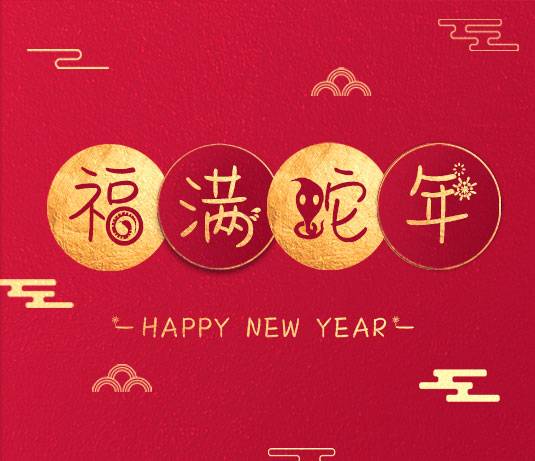
在文字设计中,设计师更注重画面各部分的充分表达,而不是作品的整体性和统一性。
(1)忽视文字和内容的合理性。人们对画面的关注从文字内容本身到文字的图形表达,侧重于画面的趣味分割和文字的非常规处理。
(2)画面呈现多中心多视点的格局,人物突破了有限空间的限制。文本解构是在看似无序的表象下。为了达到不可区分的视觉效果,需要文字与形状、形状与形状之间的高度协调,而不是每个文本解构与图像之间的混乱叠加。所以对文字的解构是设计师对这个“度”的把握,不是没有规则和度。